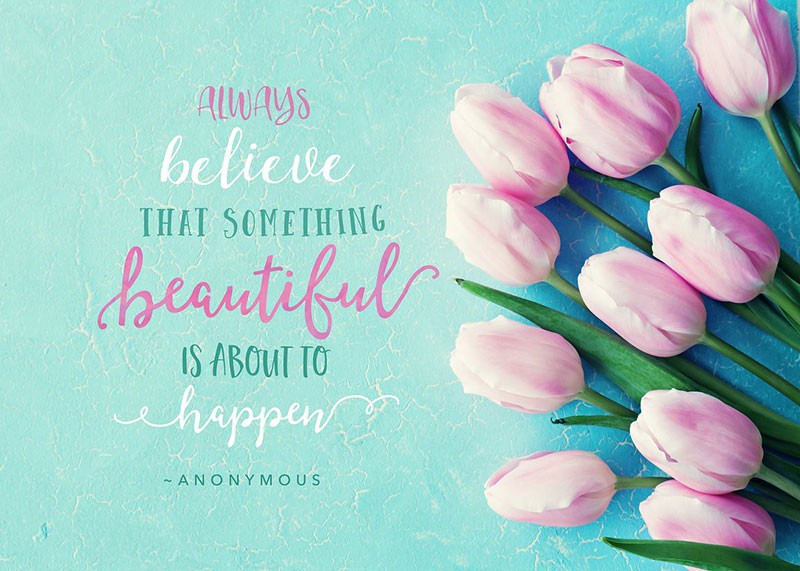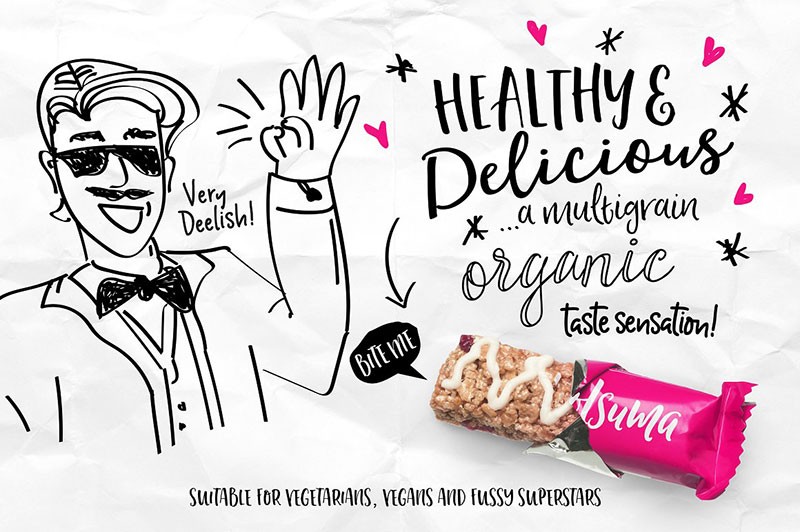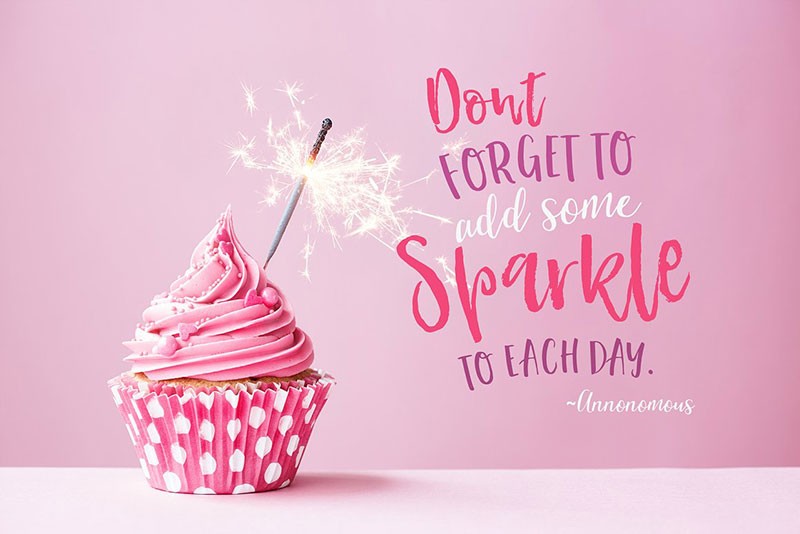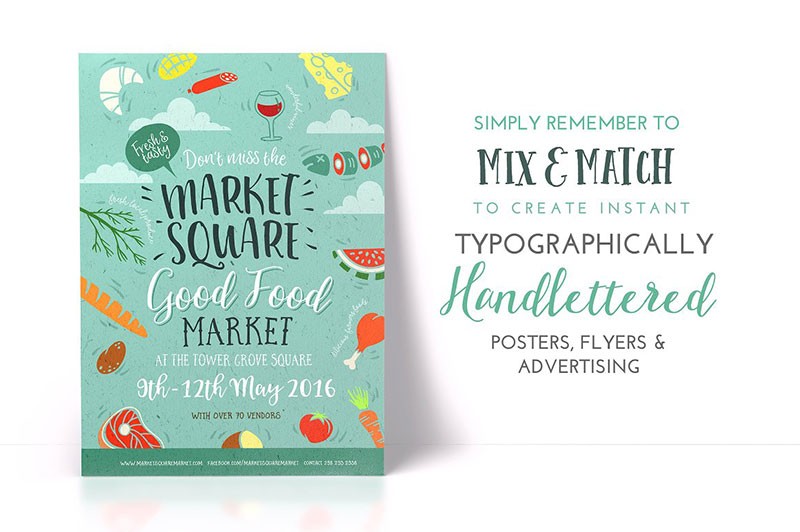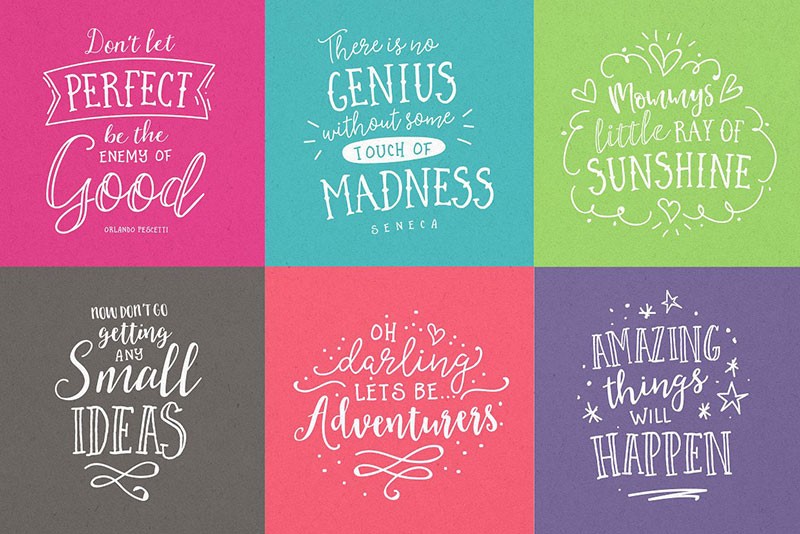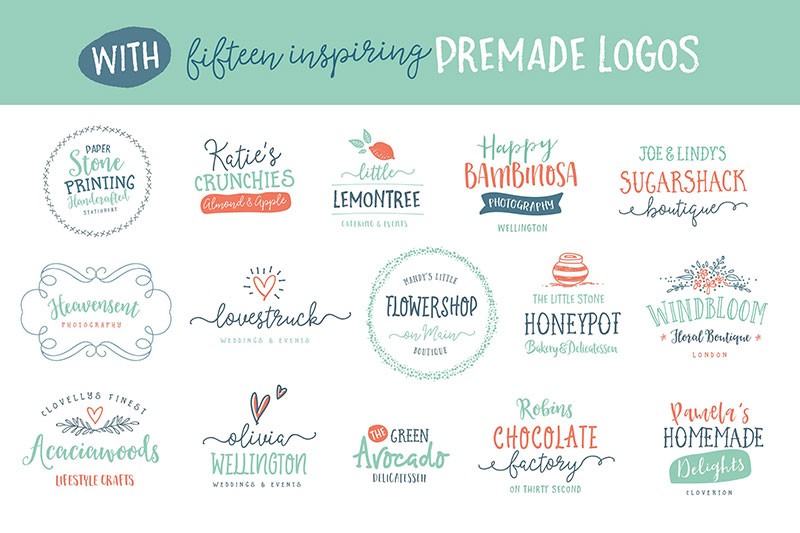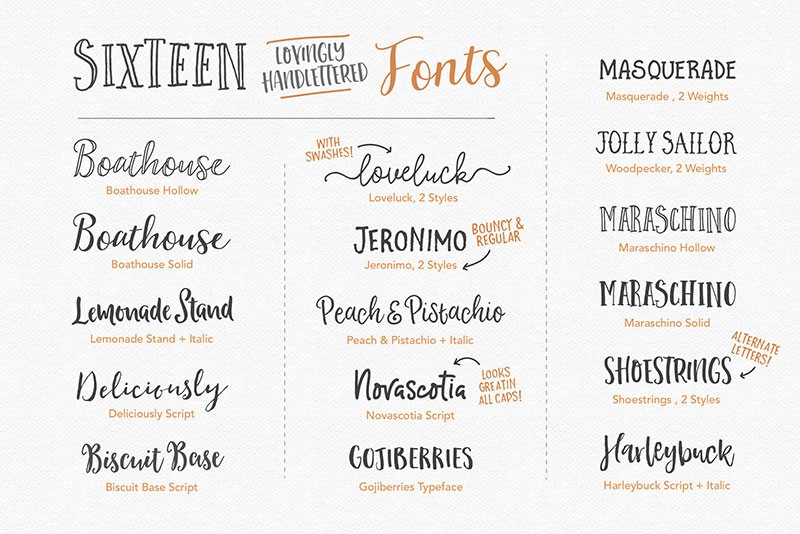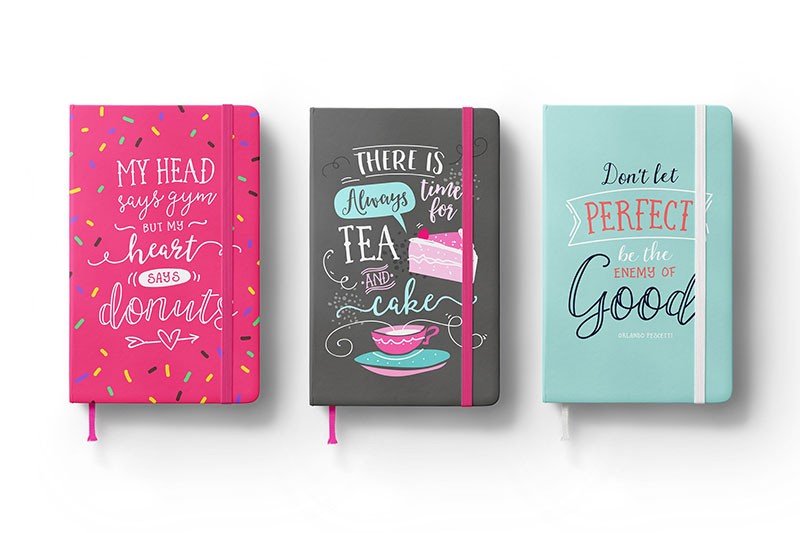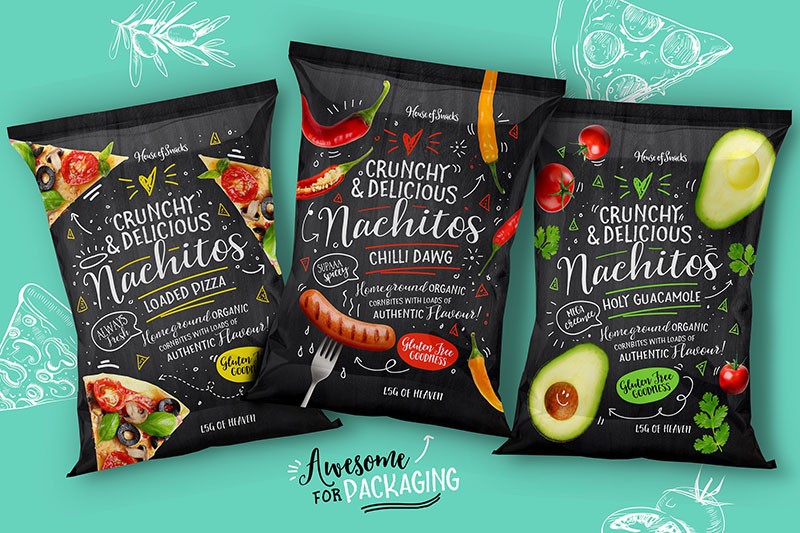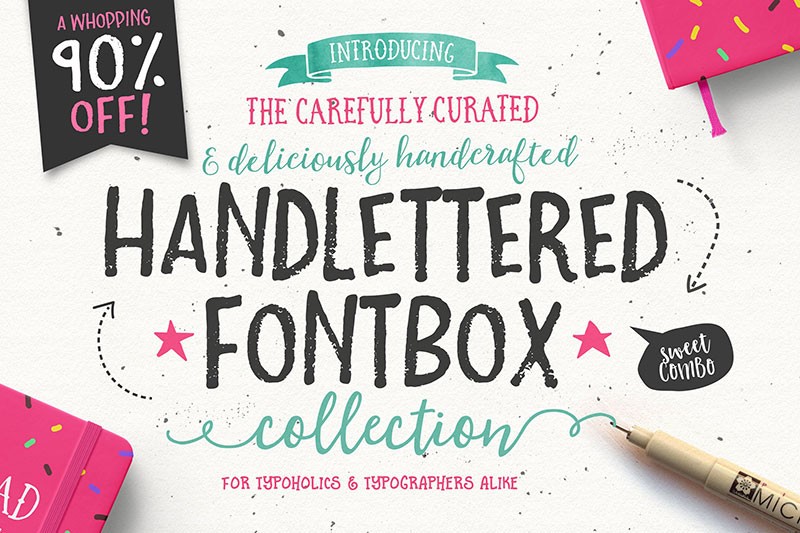
14款创意海报LOGO英文手写字体
一组创意手写风格英文字体合集,共14种主题和风格,从简约现代到浪漫华丽,应有尽有。这些手写字体不仅能够增强设计的独特性和个性化,还能让您的品牌或产品在市场上脱颖而出,令人印象深刻。这个合集不仅适用于设计师和品牌所有者,也适用于喜欢DIY设计的个人爱好者。从名片、海报到产品包装和广告,这些手写字体都能为您的设计带来独特的美感和品牌价值。